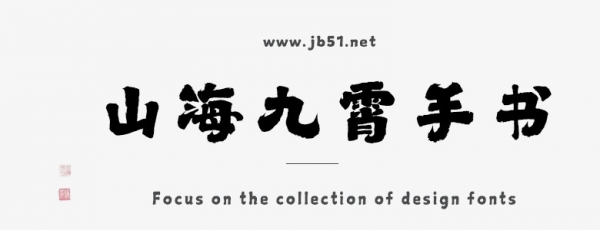
山海九霄手書W是由山海字庫出品的字體,這款字體筆觸略粗,字形大氣,具有很好的視覺感,適合應(yīng)用于藝術(shù)設(shè)計、平面宣傳設(shè)計、網(wǎng)頁設(shè)計,書法字帖等領(lǐng)域,需要的朋友可以前來本站下載。
山海九霄手書,由山海字體社出品。本字體為簡繁字庫,采用Adobe-GB1-5編碼,包含常用簡體(GB2312-80)6763個,繁體(GBK)2406個,共計9169個漢字;以及ASCIl常用西文200+。